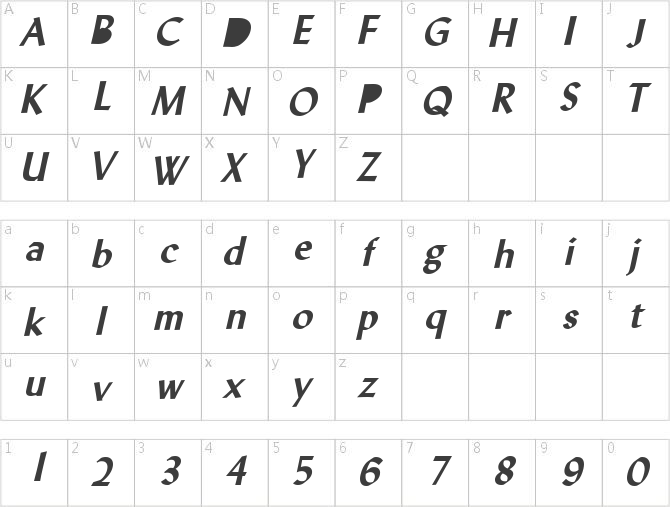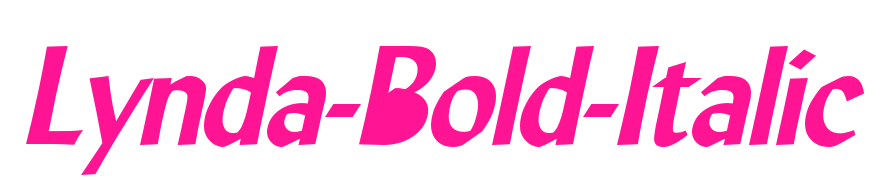
字體名稱: Lynda-B
Lynda-Bold-Italic
Lynda-Bold-Italic字體字庫是一款讓人賞心悅目、百看不厭的英文字體,適合各類廣告和產(chǎn)品包裝設(shè)計應(yīng)用,字體大小0.05MB,格式為ttf字體,上傳用戶是華大文化傳媒,作者/版權(quán)方為未知